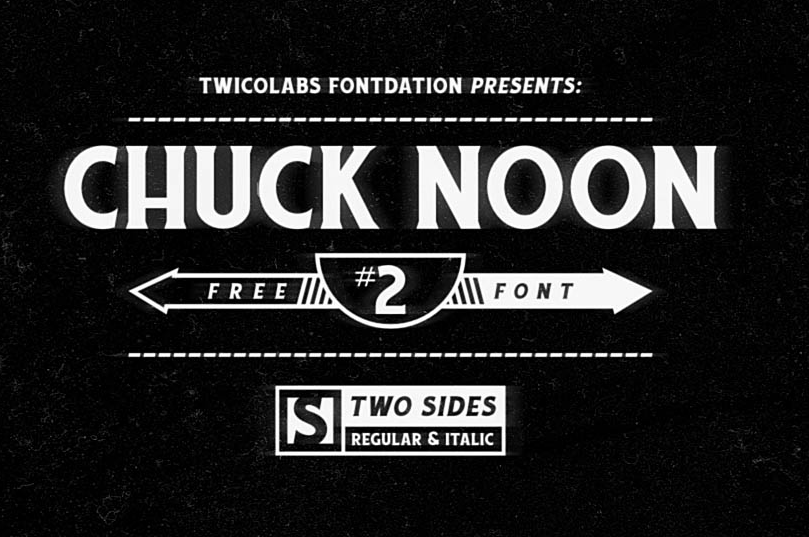
A Chuck Noon Font é uma elegante escolha para designers que buscam uma combinação de precisão e sofisticação. Proporcionada pela Twicolabs Design, esta serif font foi meticulosamente criada pelo designer Hamilton. Suas linhas reticentes e detalhes cuidadosos garantem um resultado final de alta qualidade e estética refinada. Ideal para projetos exigentes que exijam perfeição, a Chuck Noon é uma excelente adição à sua coleção de fontes. Compreender o real poder desta fonte irá transformar suas produções digitais, oferecendo você um toque final elegante e profissional em qualquer projeto.